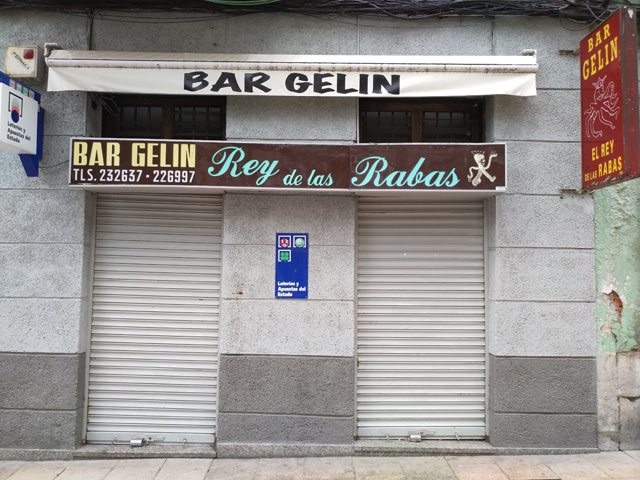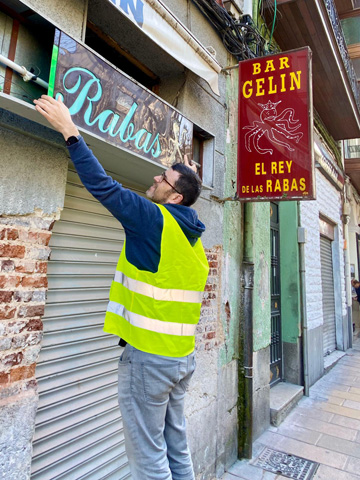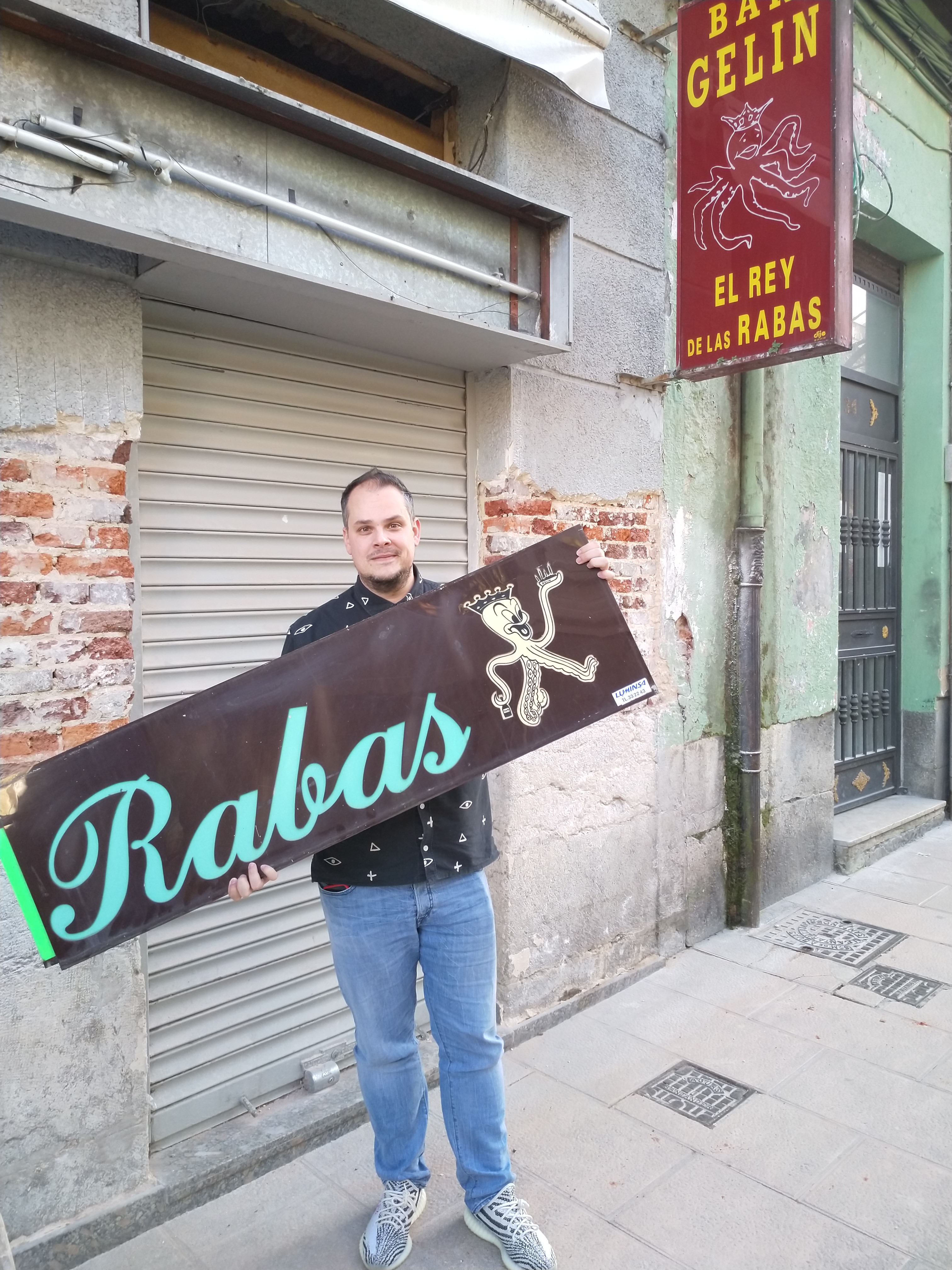
Bar Gelín. El Rey de las Rabas
El «Bar Gelín» fue un mítico de Santander que durante más de 70 años se ha convertido en un referente en las Rabas, y es uno de esos negocios que quedan en la memoria de la ciudad. Fundado en 1954 por Ángel Lanza (Padre) es su hijo, Ángel Lanza “Gelín” que llevaba en el bar desde los 15 años es quien con el tiempo se hace cargo, siendo conocido ya en la década de los setenta como “El Rey de las Rabas” porque se convirtió en un referente de este icónico aperitivo santanderino.
En 2019 cierra por jubilación y el local es vendido. Ayer, tras un aviso, pudimos ir a bajar el rótulo frontal para su preservación y exposición, como Patrimonio Gráfico. Destaca especialmente su iconografía del Pulpo con la corona. El rótulo de vela se lo ha quedado su propietario como recuerdo.